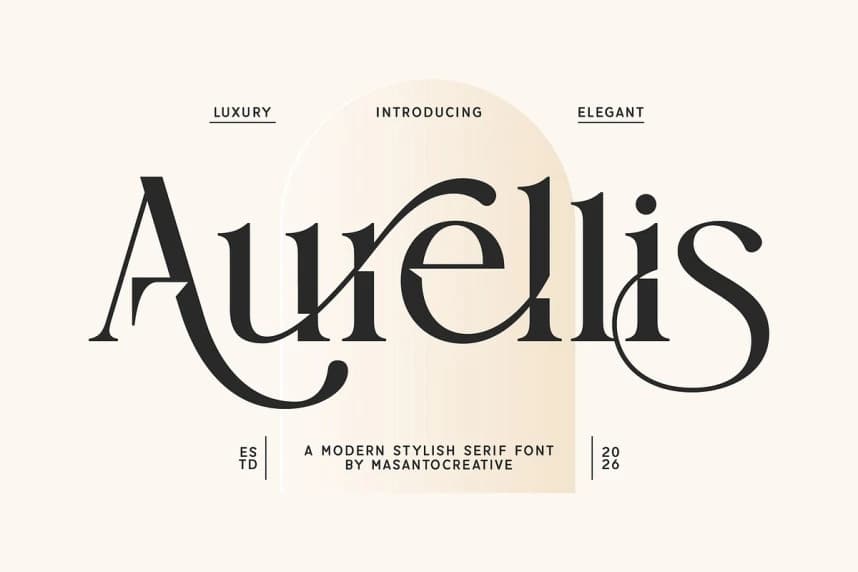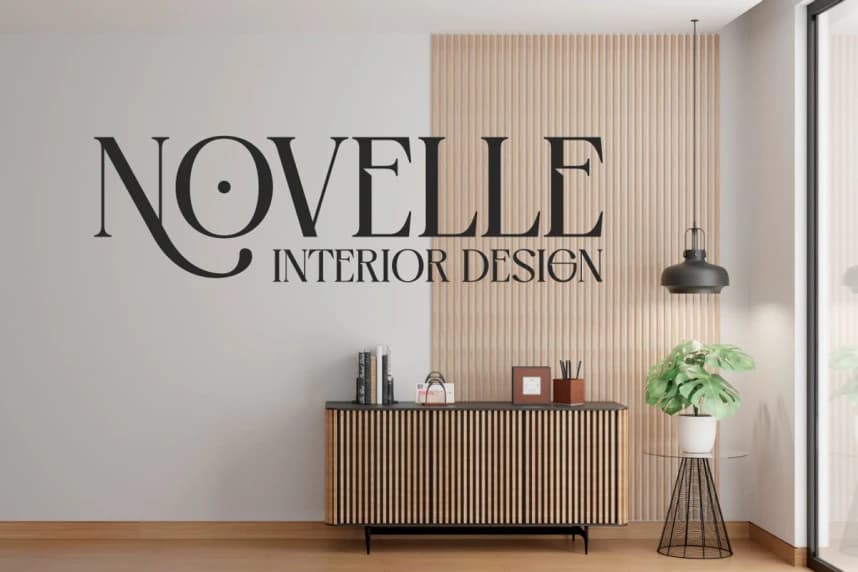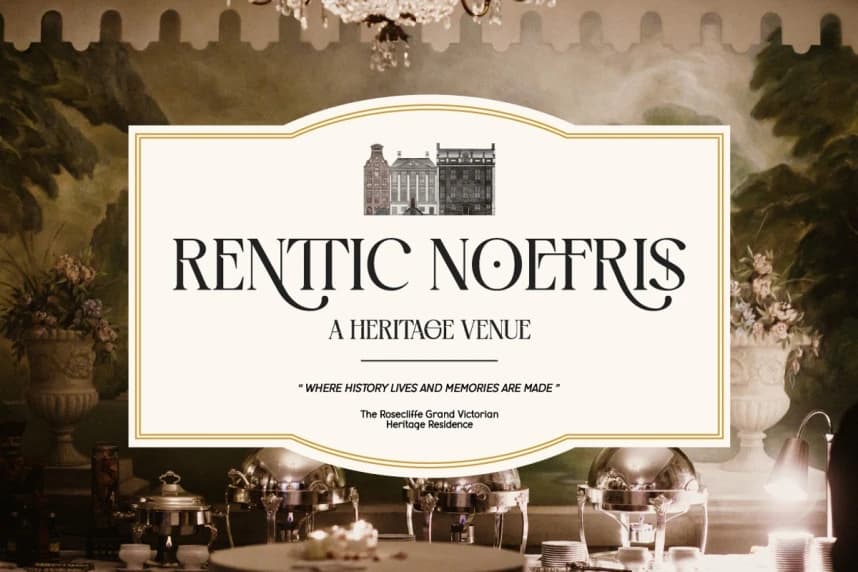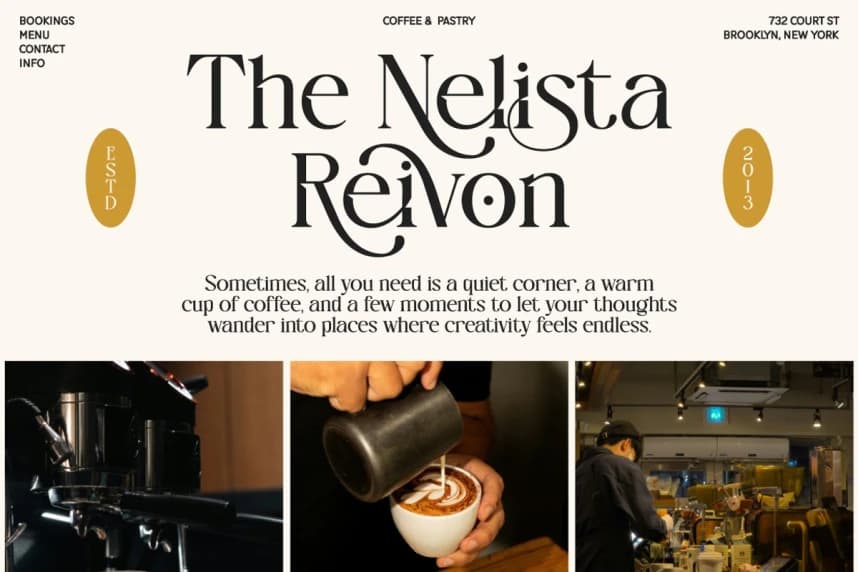
Aurellis Font
Aurellis Font, modern ve zarif bir serif yazı tipidir ve yaratıcı projelerinize lüks ve sofistike bir dokunuş katması amacıyla tasarlandı. Yüksek kontrastlı hatlar, zarif eğriler ve şık ligatürler ile bu yazı tipi markalaşma ve editoryal tasarım için mükemmeldir.
- Serif Yazı Tipi
Aurellis Font, yaratıcı projelerinize lüks ve sofistike bir dokunuş katmak için tasarlanmış modern ve zarif bir serif fontudur. Yüksek kontrastlı çizgiler, rafine eğriler ve şık ligatürler ile öne çıkan bu font, marka tasarımı ve editoryal tasarım için mükemmeldir.